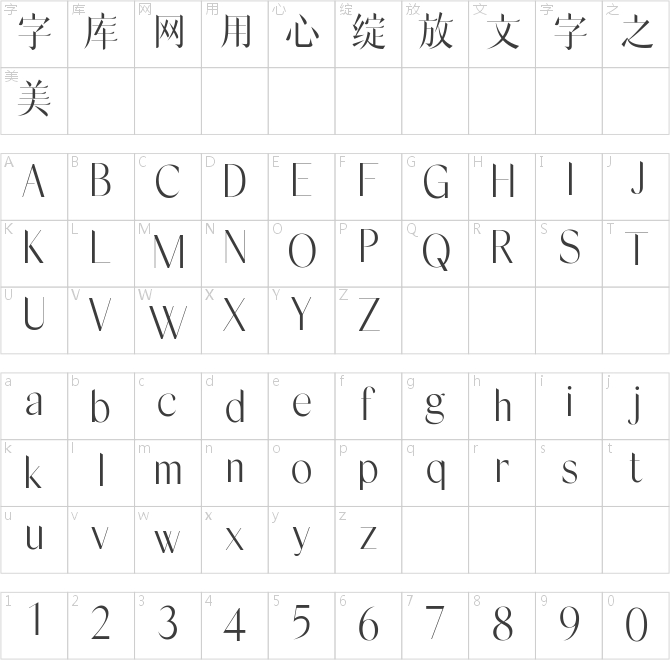
火山字型 眉月 S02 詳情頁
字體名稱: 火山字型 眉月
火山字型 眉月 S02
定位于當下視覺審美趨勢,可在標題展示類應用場景中廣泛使用。時尚、美妝、文化、娛樂等行業推薦使用。
眉月,采用傳統宋體的小中宮處理,借鑒了港臺版的舊字形風格,在體飾上盡量簡化,僅保留宋體字的基本風格。外形上縮減了字面的寬度,使其呈現出修長秀麗、優雅清新之勢。封口橫畫收筆留白,增加設計感與靈動性。各筆畫的處理犀利、清勁、峻朗、風骨兼備,整體結構清晰、脫俗、內斂,有著強烈的人文氣息。